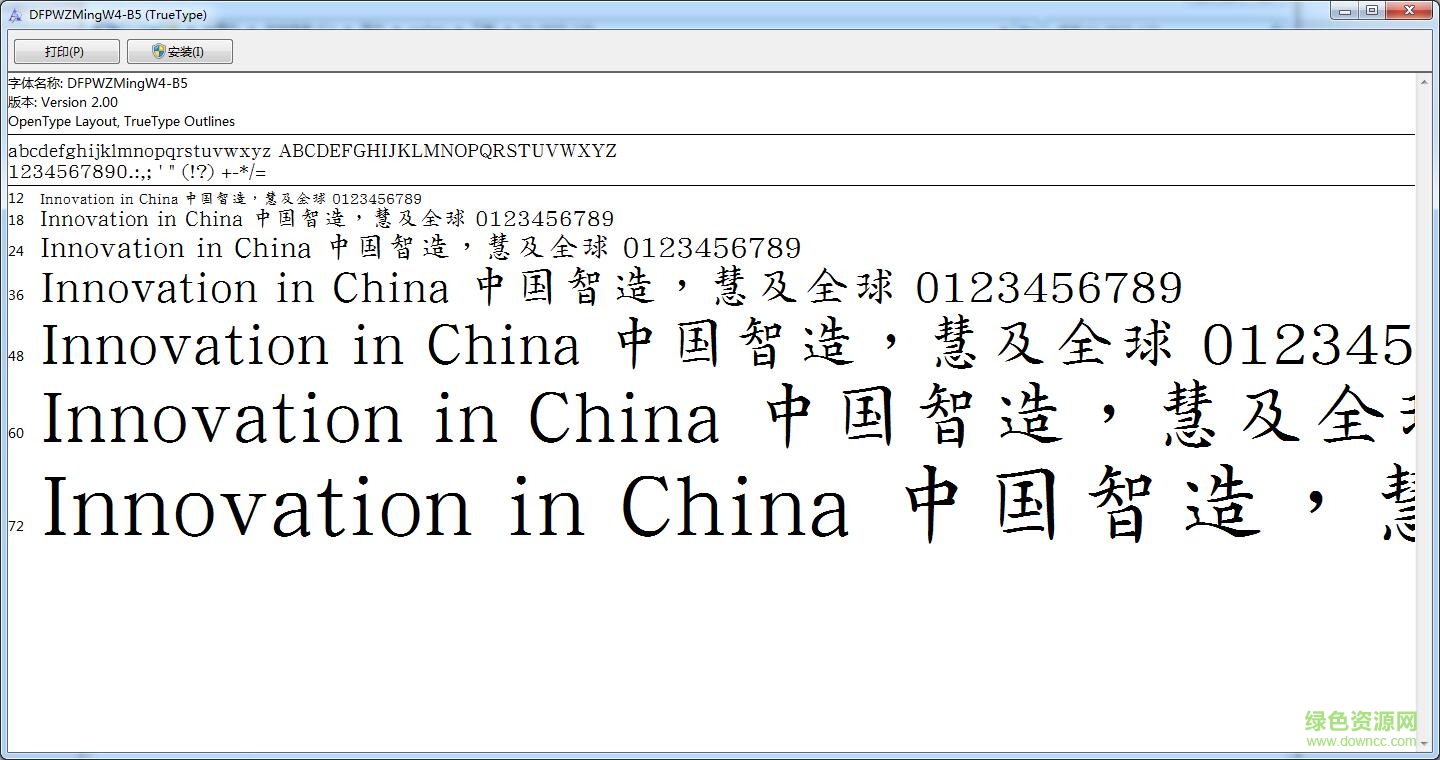
華康文徵明體w4是一款應(yīng)用于廣告創(chuàng)意設(shè)計方面的簡體中文字體,該字體字形粗細(xì)均勻,大方得體,整體效果非常出色,并且字庫完整,可以適用于名片設(shè)計、平面設(shè)計、廣告設(shè)計、報紙雜志、企業(yè)LOGO、商標(biāo)注冊、電視臺廣告等領(lǐng)域。需要的用戶快來綠色資源網(wǎng)下載吧。